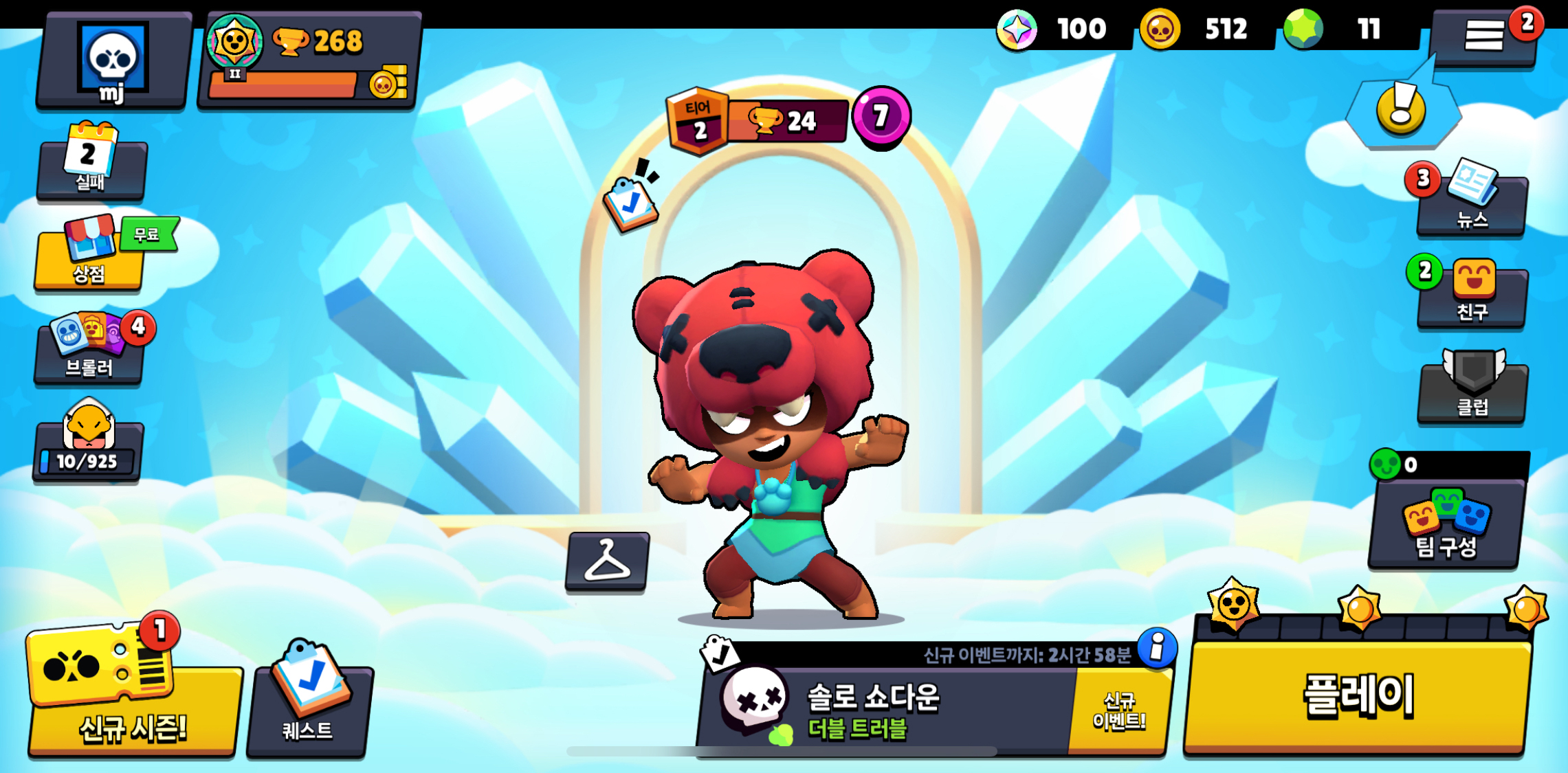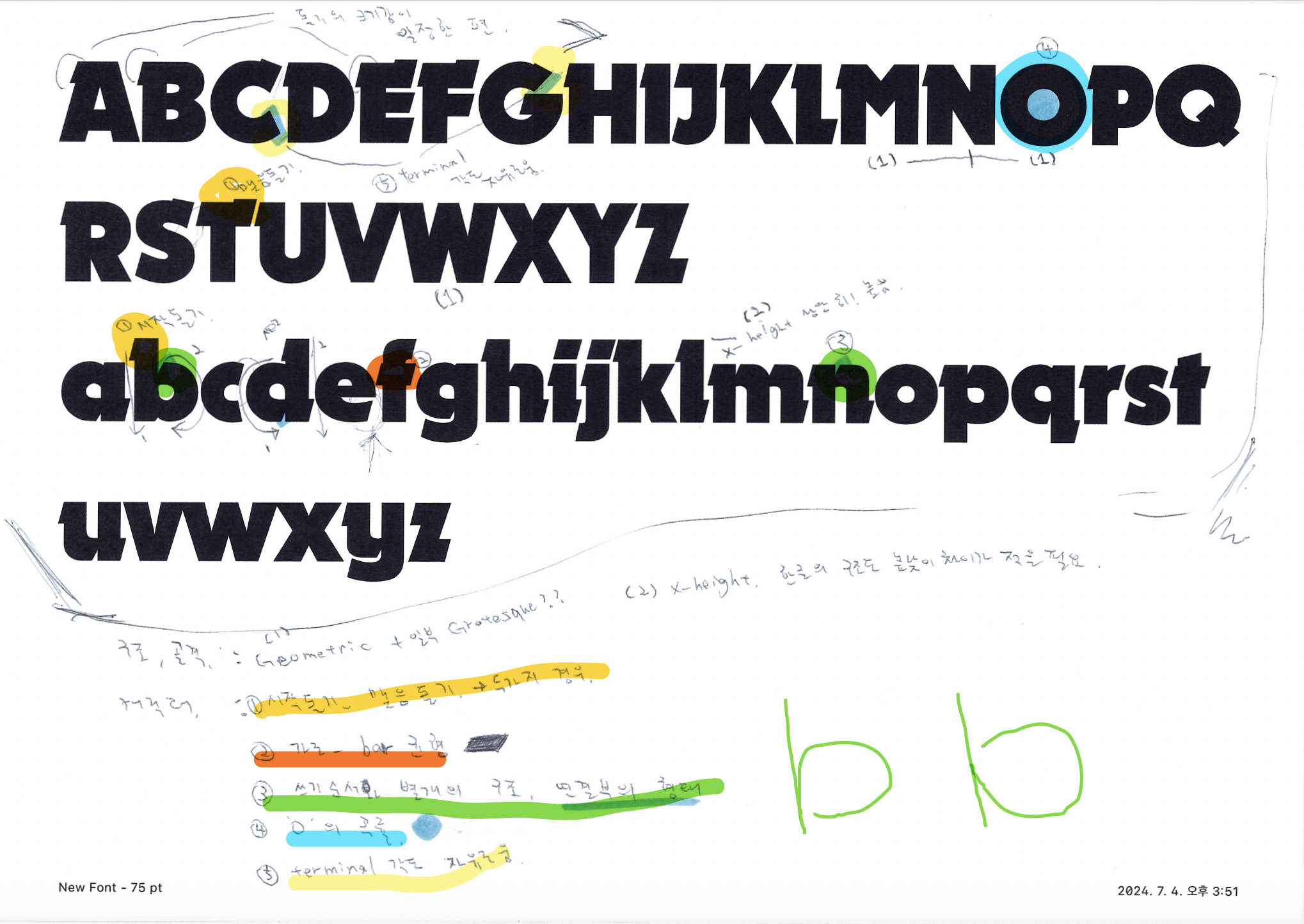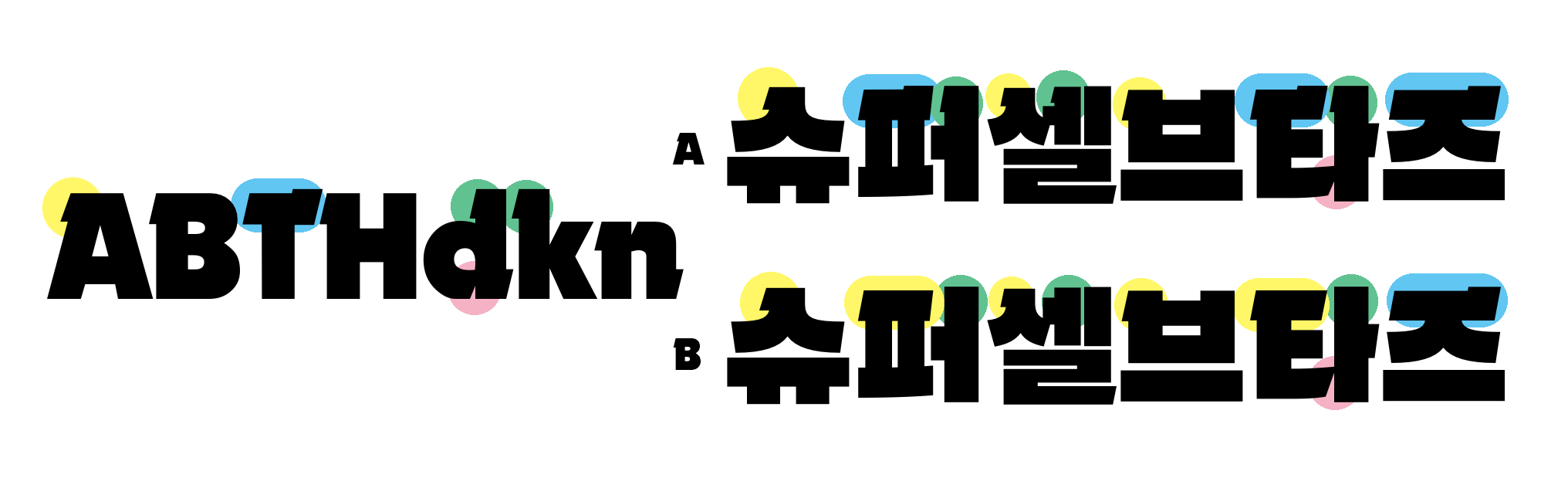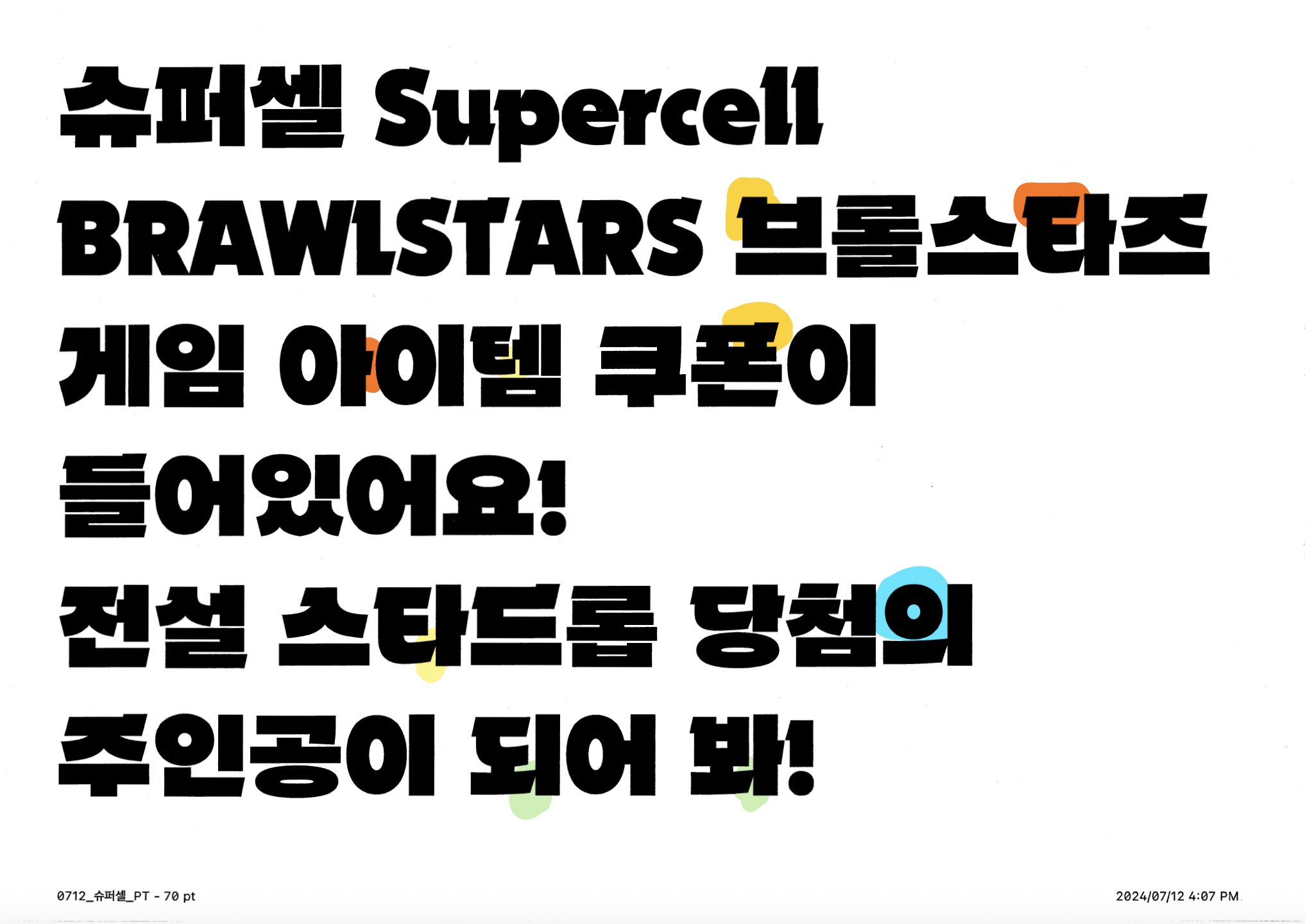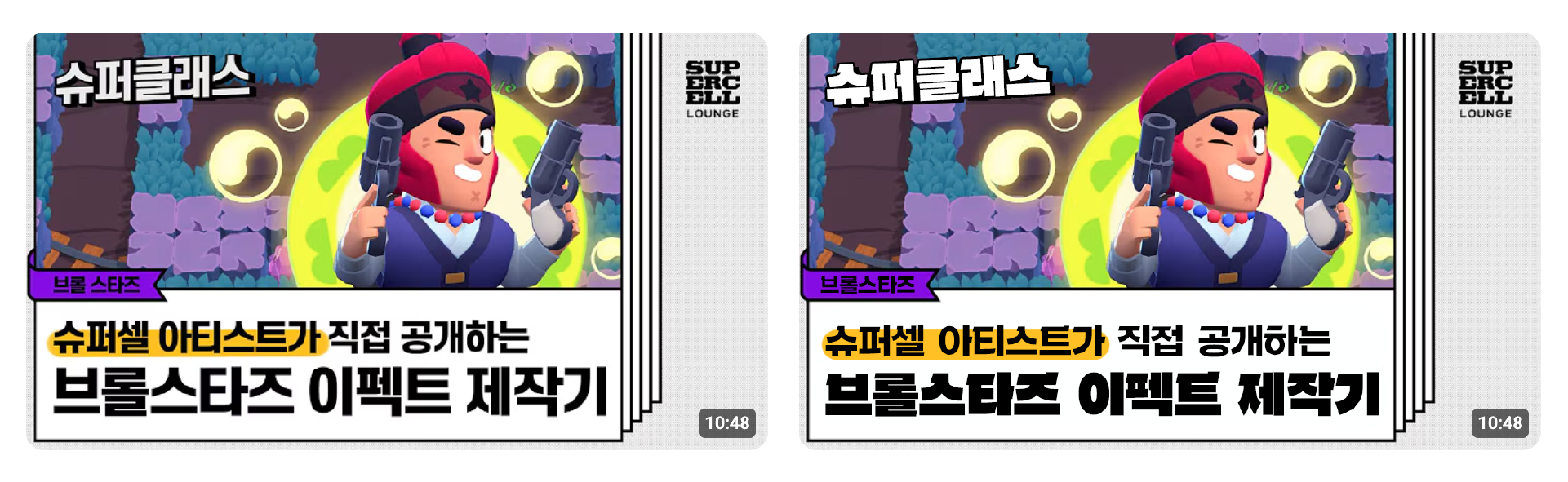
10년만의 재회
2019년 슈퍼셀이 모바일 게임 브롤스타즈를 출시한 이후, 한국에서 점차 인기를 얻고 유저들의 뜨거운 반응을 이끌어내면서 한국 시장을 겨냥한 브랜드 이미지 강화에 대한 니즈가 함께 커져갔습니다. 영어 버전에서는 브롤스타즈의 브랜드 아이덴티티를 효과적으로 전달할 수 있는 라틴 폰트가 사용되고 있었지만, 한국어 버전에서는 결이 다른 폰트를 사용하고 있었기 때문에 디자인의 일관성 측면에서 아쉬움이 남는 상황이었는데요. 이 인기에 힘입어 슈퍼셀은 브롤스타즈의 브랜드 정체성을 한국에서 더 견고히 하고자 새로운 한글 폰트 개발을 결정하면서 산돌을 찾아 주셨습니다.
브롤스타즈 게임 화면
슈퍼셀과 산돌의 인연은 약 10년 전, 인기 게임 ‘클래시 오브 클랜’의 한글 폰트(링크)를 개발하면서부터였습니다. 저는 당시에 디자인 작업에 참여했고 업무의 일환으로 게임을 플레이하기 시작했습니다. 작업을 하면서 점점 슈퍼셀의 게임과 세계관에 매료되었고 어느새 열성적인 유저이자 팬이 되어 있었습니다. (그때부터 지금까지, 게임도 매일 즐기고 있답니다 :-)
당시 폰트 개발 이후 몇 차례의 업데이트와 소통 과정이 있었지만, 이번에 다시 슈퍼셀의 게임 폰트 개발을 함께하게 되어 정말 기뻤습니다. 특히 산돌과 폰트를 개발하는 것으로 확정되었을 때의 기쁨은 더욱 컸습니다. 좋아하는 게임, 좋아하는 회사와 함께하는 일이기에 자연스레 즐거이 디자인에 참여했습니다.
클래시 오브 클랜 게임 화면
라틴 → 한글 매칭 디자인
산돌에서는 다양한 언어의 폰트를 개발하고 있습니다. 한글, 라틴 알파벳, 키릴, 한자 등. 두 가지 이상 언어의 폰트를 개발할 때는 고객사에게 가장 주요한 언어의 문자를 먼저 디자인하게 되는데요. 국내 고객사가 폰트 개발을 의뢰하는 경우 한글을 우선적으로 디자인할 때가 많습니다. 반면에, 해외 고객사가 폰트 개발을 의뢰하는 경우 해외 현지의 사용을 우선하여 라틴 알파벳을 먼저 디자인할 때가 많고, 해당 라틴 디자인에 한글을 매칭하는 순서로 진행되고는 합니다.
산돌은 해외 고객사의 폰트 개발 경험이 많기 때문에 이런 방식에 익숙한데요. 브롤스타즈 프로젝트 역시 동일한 흐름이었습니다. 앞서 언급한 것과 같이 영어 버전에서는 이미 브롤스타즈의 브랜드 아이덴티티를 잘 나타내주는 라틴 폰트가 사용되고 있었고, 이에 어울리는 한글 디자인을 저희에게 요청해 주셨습니다. 이런 경우 디자인은 보통 다음과 같은 순서로 진행됩니다.
라틴 디자인 분석
분석된 특징을 바탕으로 한글 디자인, 테스트
해석(의역)과 다듬기
우선 라틴의 구조와 캐릭터를 나눠 분석합니다. 예를 들어, 휴머니스트인지 지오메트릭 계열인지, 글자의 폭, 공간의 개방 정도, 골격은 어떤지 등을 파악하며, 세부적인 표현 방식과 구조적 연결성도 함께 살펴봅니다.
이후 분석된 특징을 한글에 적용해 보고 테스트와 반복적인 다듬기를 거칩니다. 때로는 라틴의 특징을 직접적으로 적용하기도 하지만, 무리하게 억지로 옮기기보다는 자연스럽게 스며들도록 고민하는 편입니다. 저는 이 고민 과정을 종종 ‘의역하기’라고 표현하곤 합니다. 문장을 그대로 번역하는 직역보다 맥락과 어감에 맞춰 자연스럽게 다듬는 작업이 의역과 닮아있지 않나요?
그래서 어떻게 매칭을?
이번 프로젝트에서는 「브롤 디스플레이체」와 「브롤 고딕체」 두 가지 스타일을 개발했습니다. 이 글에서는 「브롤 디스플레이체」 위주로 디자인 과정을 소개해 보겠습니다.
구조 분석
라틴 소문자의 엑스하이트(x-height)가 상대적으로 높은 점이 눈에 띄었습니다. 이는 대문자와 소문자의 높낮이 차이, 어센더(ascender)와 엑스하이트의 간격이 크지 않다는 뜻이죠. 이러한 설계에는 한글도 높낮이 차이가 적은 ‘네모꼴 구조’가 잘 어울릴 것이라고 판단했습니다.
라틴 분석, 특징 확인
특징 분석과 해석
상기 이미지에 표시된 라틴 알파벳의 캐릭터들을 확인할 수 있었고, 이를 한글로 디자인할 때 어떻게 자연스럽게 표현할 수 있을지를 고민하며 테스트 했어요. 그런 고민 중 하나를 적어보자면, 라틴에서는 기둥(Stem)에 돌기 형태의 디테일이 전체적으로 들어가 있었지만, 한글의 경우 홀자 기둥(ㅏ,ㅣ 등의 세로획)에 그대로 적용하면 지나치게 반복되거나 불필요하게 복잡해 보일 수 있었습니다.(A) 특히 굵은 웨이트이기 때문에 더 그럴 수 있다고 판단했죠. 그래서 닿자에만 돌기 요소를 적용하되, 첫 닿자에만 사용한다는 규칙을 메인으로 세워 빈도수를 조절했습니다.(B)
직역이라면 A와 같이 표현될수도 있을 것 같아요. 「브롤 디스플레이체」는 B와 같이 디자인 되었답니다.
라틴 특징을 적용해 본 초기 한글 디자인
활자와 확산
폰트 개발이 시작되면서 슈퍼셀이 준비하고 있는 주요 온・오프라인 캠페인에 우선 적용하기 위한 작업도 병행되었습니다. 고객사의 중요한 일정에 맞춰야 할 경우, 폰트 전체를 완성하기 전에 필요한 일부 글자만 우선 제작하여 사용하는 방식이 종종 활용되곤 합니다. 개발 중인 활자가 실시간으로 사용되는 모습을 보면 폰트를 지칭하는 ‘활자活字’ 뜻 그대로 ‘생명이 깃든다’는 표현이 절로 떠오르곤 합니다.
이번 프로젝트 또한 필요 글자를 실시간으로 요청해 주셨는데요. 다행히도 무리 없이 대응할 수 있는 상황이었기 때문에 제작된 글자는 이벤트를 위한 디자인에 적용되었습니다. 슈퍼셀에서는 해당 디자인 이미지를 공유해 주시거나 이벤트에서 사용된 실물을 전달해 주시기도 했습니다.
브롤스타즈 × 켈로그 콜라보 캠페인에 신규 폰트 적용!
그리고 개발 시작 후 약 8개월, 한국에서의 브롤스타즈 브랜딩을 더 강화하고 아이덴티티를 명확하게 보여줄 수 있는 한글 폰트의 개발이 완료되었습니다. 글자를 만들며 균형을 다듬고, 새로운 글자를 만들고, 조합에 따라 새로이 균형을 다듬고... 반복되는 인고의 시간이기도 했습니다.
아래 게임 로고 + 「브롤 디스플레이체」 + 「브롤 고딕체」 적용 이미지, 그리고 Before-After를 보면 어떤가요? 한글 디자인과 브랜드 이미지, 게임 캐릭터가 일관되어 보이시나요?
어린이날 개최된 브롤스타즈 DAY에 신규 폰트 적용!
Before 기존 유튜브 썸네일 → After 「브롤 디스플레이체」 적용